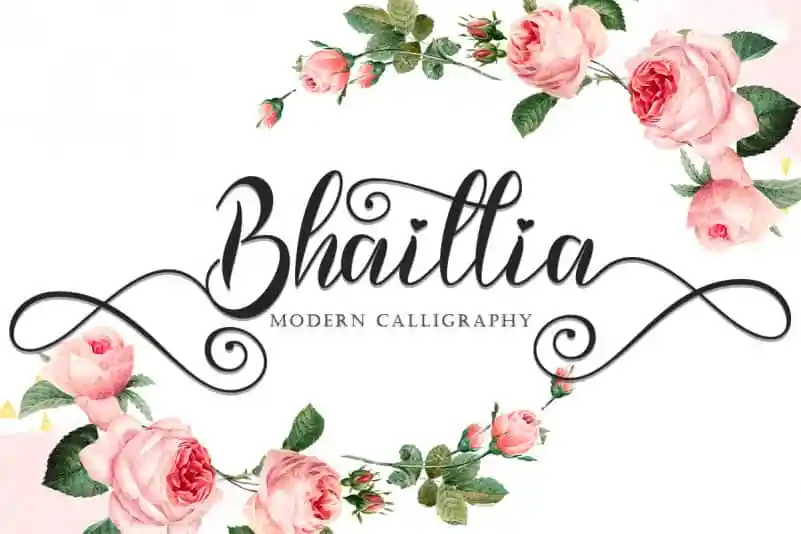
Bhaillia Calligraphy Font – Download Grátis
A Bhaillia Calligraphy Font é uma opção perfeita para quem deseja dar um toque elegante a suas criações digitais. Escrevendo diretamente com sua caligrafia, Yoga Letter criou esta font que pode ser utilizada em uma variedade de projetos, desde invitations de casamento até promoções empresariais e designs pessoais. Ideal para as mais variadas ocasiões, seja para aniversários, natal ou valentine, essa font é a escolha certa para tornar qualquer palavra romântica ou frase memorável uma parte do seu design. Ela também é perfeita para personalizar marcas e logotipos, estampas de material de decoração ou até mesmo um status nas redes sociais. Com sua beleza única e elegante, a Bhaillia Calligraphy Font será um complemento inovador para qualquer projeto que você está trabalhando.